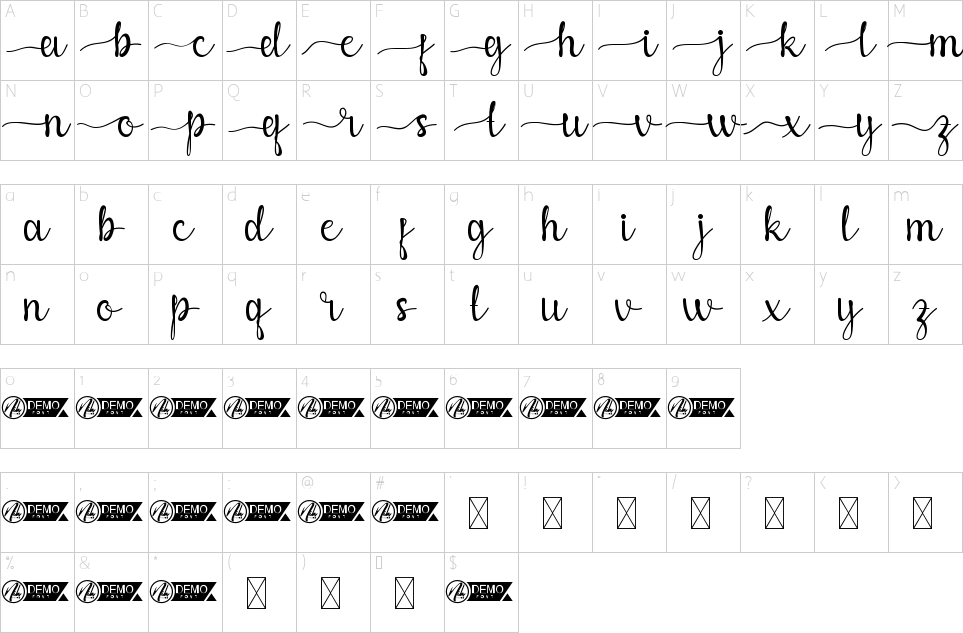
Descubra a beleza da fonte Putra Putri no site 1001 Free Fonts. Esta elegante fonte é um presente gratuito para todos os amantes de design, especialmente aqueles que buscam uma variedade de opções para seus projetos. Desenvolvida pelo designer desconhecido nihstudio, Putra Putri oferece um estilo moderno e sofisticado que pode ser facilmente integrado em qualquer projeto digital, seja para criar logos, textos publicitários ou até mesmo para fazer design gráfico. Com seu design único e detalhado, Putra Putri pode ajudá-lo a destacar seus trabalhos e garantir que eles estejam impecavelmente alinhados. Desfrute do seu download e experimente a versão para Windows e Mac hoje. Se você está procurando por uma fonte que ofereça tanto estilo quanto facilidade de uso, a Putra Putri é uma ótima escolha para você.